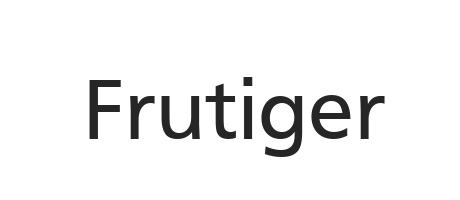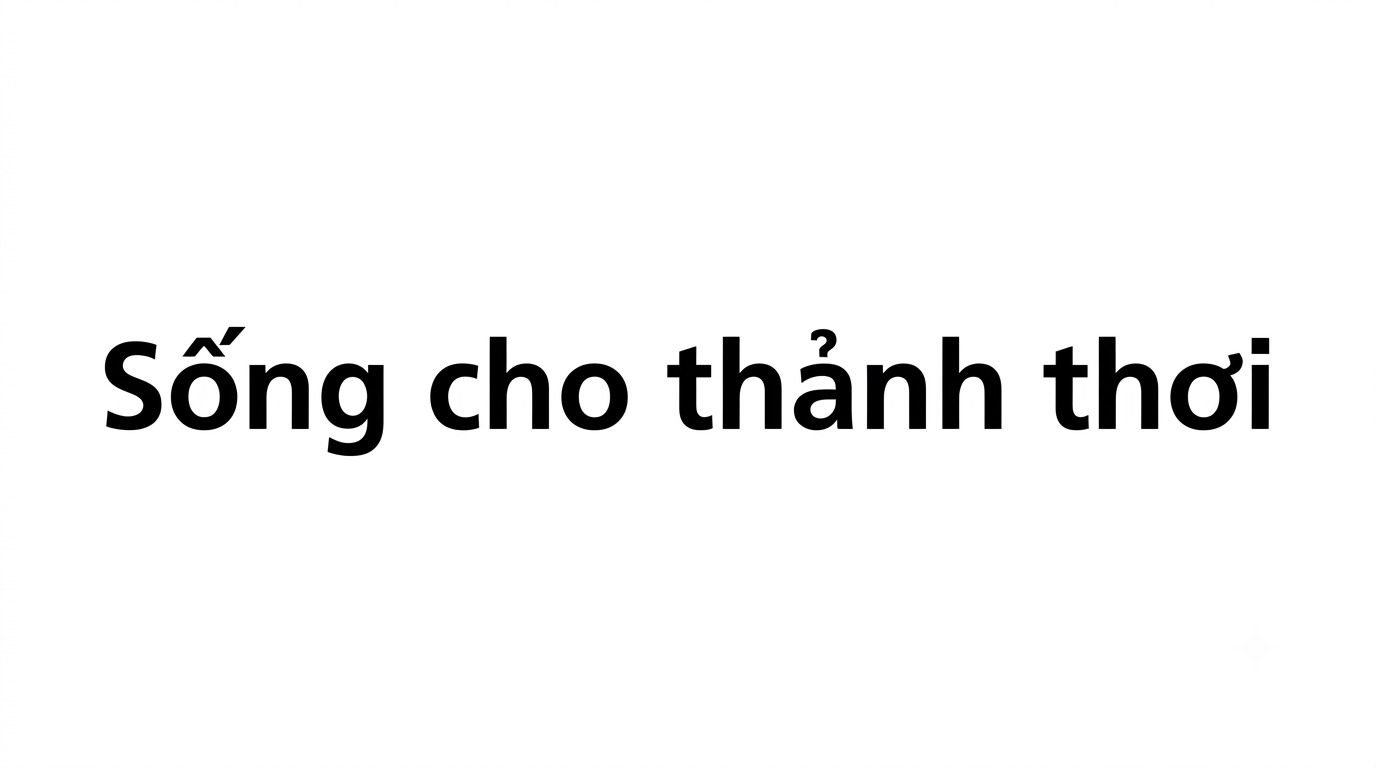
Nhiều designer gặp rắc rối khi sử dụng font Frutiger do một số phiên bản bị lỗi dấu tiếng Việt, thiếu ký tự hoặc đường nét bị vỡ khi phóng lớn để in ấn biển hiệu, bảng nhận diện thương hiệu. Những lỗi này khiến tổng thể thiết kế mất đi sự rõ ràng, làm giảm tính chuyên nghiệp của doanh nghiệp trong mắt khách hàng và đối tác.
Xưởng In Viva cung cấp bộ Frutiger font Việt hóa sắc nét, đầy đủ nhiều biến thể kiểu chữ, hỗ trợ hiệu quả cho quá trình thiết kế bao bì, in logo quà tặng và xây dựng hệ thống nhận diện thương hiệu chuyên nghiệp.
Font Frutiger là gì?
Font Frutiger là một trong những phông chữ thuộc dòng Sans-serif (chữ không chân) thành công mọi thời đại, được thiết kế bởi huyền thoại Adrian Frutiger vào năm 1975. Ban đầu, phông chữ này được tạo ra dành riêng cho hệ thống biển chỉ dẫn tại sân bay quốc tế Charles de Gaulle ở Paris. Đặc điểm nổi bật của Frutiger là khả năng hiển thị rõ ràng, dễ đọc ngay cả ở khoảng cách xa hoặc trong điều kiện ánh sáng yếu.
Trong giới thiết kế, Frutiger Family được mệnh danh là bộ phông chữ “nhân bản” bởi cấu trúc chữ mang tính hình học nhưng vẫn giữ được sự ấm áp và linh hoạt. Hiện nay, bộ font này đã phát triển thành nhiều phiên bản đặc thù như Frutiger Aero với phong cách bóng bẩy của thập niên 2000, hay Frutiger Metro mang hơi hướng hiện đại của đô thị. Tại Việt Nam, việc tìm kiếm bản Frutiger việt hóa chuẩn giúp đảm bảo các slogan doanh nghiệp giữ được tính thẩm mỹ nguyên bản.
Lưu ý: Frutiger có rất nhiều biến thể độ dày khác nhau. Khi thiết kế tiêu đề trên bao bì hộp cứng cao cấp, bạn nên chọn phiên bản Bold hoặc Black để tạo cảm giác quyền uy và tin cậy cho thương hiệu.
5 Ứng dụng của font Frutiger việt hóa trong thiết kế và in ấn
Vẻ đẹp hiện đại, rõ ràng và dễ nhận diện của Frutiger giúp nâng cao tính chuyên nghiệp cho nhiều sản phẩm thiết kế doanh nghiệp khi kết hợp cùng các công nghệ in ấn và gia công tại Xưởng In Viva:
- Thiết kế bao bì dược phẩm và sản phẩm công nghệ: Frutiger phù hợp để trình bày tên sản phẩm, thông tin hướng dẫn sử dụng hoặc thông số kỹ thuật trên hộp giấy. Cấu trúc chữ dễ đọc giúp nội dung hiển thị rõ ràng, phù hợp với các thương hiệu yêu cầu sự chính xác và tin cậy.
- Sản xuất set quà tặng văn phòng in logo: Logo sử dụng font Frutiger khi in UV trên bình giữ nhiệt kim loại, sạc dự phòng hoặc sổ tay da tạo cảm giác tối giản, chuyên nghiệp. Kiểu chữ gọn gàng phù hợp với hình ảnh nhận diện của các doanh nghiệp trong lĩnh vực tài chính, công nghệ và dịch vụ.
- In ấn túi giấy thương hiệu ngân hàng và doanh nghiệp: Frutiger được sử dụng để thể hiện tên thương hiệu, địa chỉ hoặc slogan trên túi giấy Ivory, Kraft. Nét chữ cân đối giúp bộ nhận diện giữ được sự thanh lịch, hiện đại và dễ ghi nhớ khi xuất hiện trong các sự kiện, hội nghị.
- Trang trí bảng hiệu và không gian showroom: Với định dạng vector, font Frutiger có thể phóng lớn trên bảng hiệu, backdrop hoặc khu vực trưng bày mà vẫn giữ được độ sắc nét. Điều này giúp doanh nghiệp duy trì sự đồng nhất giữa thiết kế kỹ thuật số và sản phẩm thực tế.
- Sản xuất kỷ niệm chương và quà tặng vinh danh: Các biến thể như Frutiger Bold phù hợp để khắc tên cá nhân, chức danh hoặc thông tin sự kiện trên pha lê, kim loại. Đường nét rõ ràng giúp nội dung khắc laser dễ quan sát và giữ được vẻ trang trọng cho món quà.
5 lưu ý khi sử dụng font chữ Frutiger việt hóa
Để bản thiết kế Frutiger hiển thị rõ nét và phù hợp với từng phương pháp in ấn, designer nên chú ý các yếu tố kỹ thuật sau:
- Lựa chọn biến thể font phù hợp với mục đích sử dụng: Frutiger có nhiều phiên bản như Light, Regular, Bold và Black. Với phần nội dung nhỏ trên bao bì, nên ưu tiên Regular để đảm bảo khả năng đọc; trong khi logo, tiêu đề hoặc slogan có thể sử dụng Bold để tạo điểm nhấn.
- Tối ưu đường Path cho gia công bế nổi: Khi sử dụng Frutiger để dập nổi logo trên hộp quà cao cấp, file thiết kế cần được xử lý các điểm neo và đường cong trong vector. Việc này giúp khuôn bế tạo hình chính xác, hạn chế tình trạng méo nét hoặc ảnh hưởng đến bề mặt giấy mỹ thuật.
- Kiểm soát khoảng cách ký tự (Kerning): Mặc dù Frutiger được thiết kế với khả năng đọc tốt, nhưng khi in trên các sản phẩm có diện tích nhỏ như bút ký, bình giữ nhiệt hoặc tem nhãn, designer nên điều chỉnh khoảng cách giữa các ký tự để chữ không bị bí hoặc dính nét.
Có. Đội ngũ thiết kế của In Viva hỗ trợ tư vấn cách lựa chọn kiểu chữ, bố cục và phương án gia công phù hợp để tạo ra sản phẩm bao bì hoặc quà tặng đồng bộ với nhận diện thương hiệu.